안병국의 웹타이포그래피 – FOOTER 디자인
웹사이트에서 콘텐츠 제공자 주소와 콘텐츠 저작권 표시를 담는 FOOTER 부분은 디자인을 마무리 짓는 부분이자, 디자인의 수준을 평가할 수 있는 핵심 부분이기도 하다. 간단한 텍스트 나열로 생각하고 쉽게 넘어갈 수 있는 부분이지만, 이에 대한 처리를 통해 디자이너의 타이포 처리 능력은 물론, 그리드 개념과 세밀함 까지 엿 볼 수 있기 때문이다.
FOOTER에는 일반적으로 로고, 주소, 저작권 표시 및, Family Site, 사이트 이용과 관련된 메뉴들이 위치하게 되는데, 이들이 사이트에서 차지하는 비중이 그리 높지 않기 때문에 GRAY계통의 단일 톤으로 처리되는 경우가 많으며, 가독성에 그리 큰 비중을 두지 않는 경우가 많다.
그러나 콘텐츠로서의 중요도와는 별개로 디자인적 측면에서 볼 때, 전체적인 디자인의 흐름을 끝맺고 콘텐츠의 정렬을 정리해 주는 역할을 수행하기 때문에 매우 중요한 부분이라 할 수 있다.
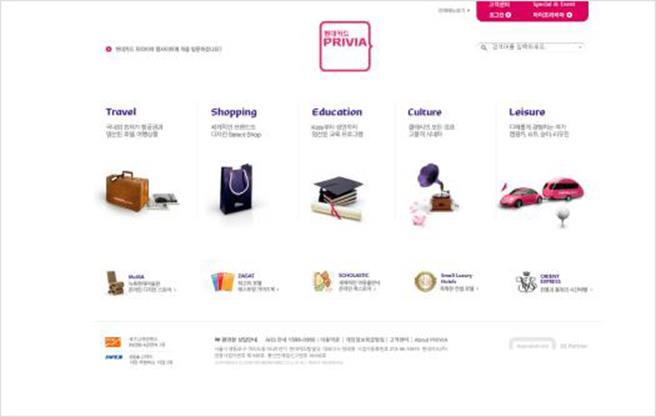
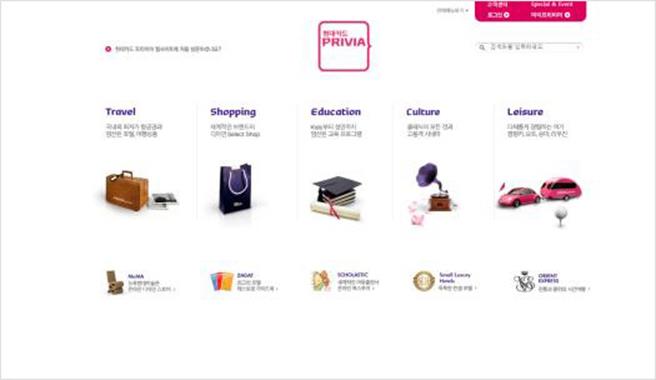
두 그림을 비교해 보면 FOOTER처리가 된 디자인이 훨씬 더 안정적이란 느낌이 들 것이다. 이는 FOOTER를 통해 밑으로 흘러가는 시선을 마무리 지어줌으로 사용자의 시선이 오른쪽으로 자연스럽게 흘러가면서 마무리 될 수 있으며, 마무리 되어주는 시점에 기업로고를 강하지 않으면서도 은은하게 보여줌으로써 편안한 마무리 처리가 가능하게 해주기 때문이다.
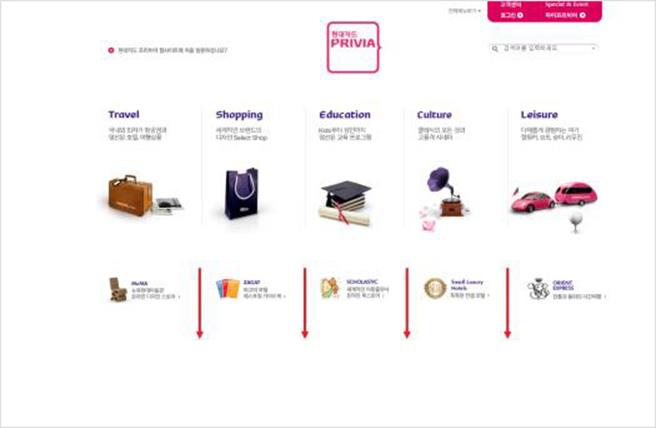
▲ 시선이 아래쪽으로 여러개 분산되어 나뉘어 지고 있는 모습
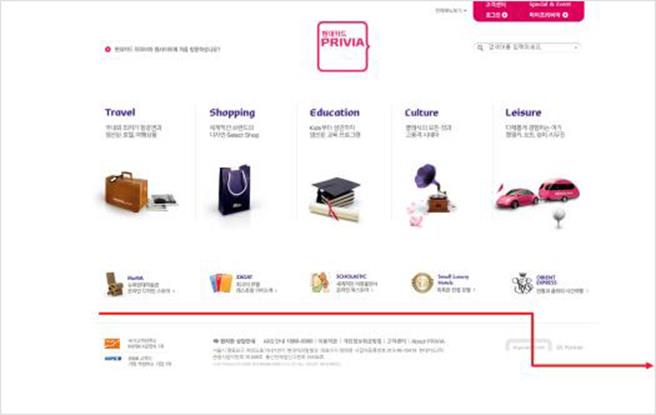
▲ 시선이 하단 FOOTER를 따라 흐르면서 오른쪽 로고에서 마무리되는 모습
이처럼 하단 FOOTER의 사용을 통해 디자인의 전체 균형을 안정화 시키고, 디자인을 좀 더 세련되게 마무리 할 수 있는데, 이것은 이 사이트처럼 FOOTER부분의 깔끔한 마무리가 전제되었기 때문에 가능한 것이라 볼 수 있다.
상단 콘텐츠를 방해하지 않는 배치된 로고와 메뉴 주소 COPYRIGHT부분의 적절한 여백 등이 조화롭게 배치되어 있는 가운데에서도 가독성을 크게 훼손하지 않는 범위 내에서 컬러 및 크기 조절이 세련되게 디자인 되어있다.
그렇다면 다음 그림들을 보고 여러분들은 어떠한 문제점들을 발견할 수 있겠는가?
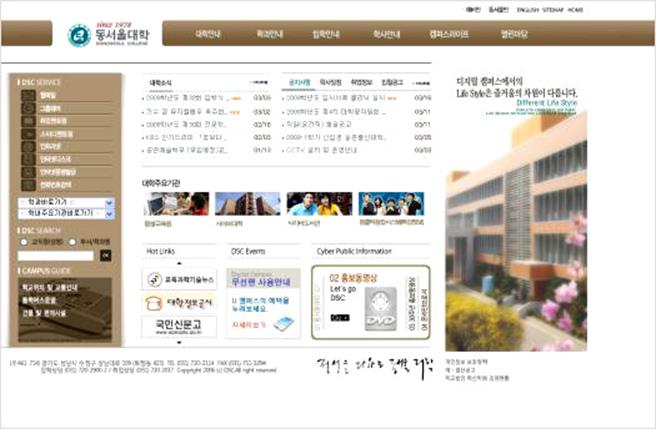
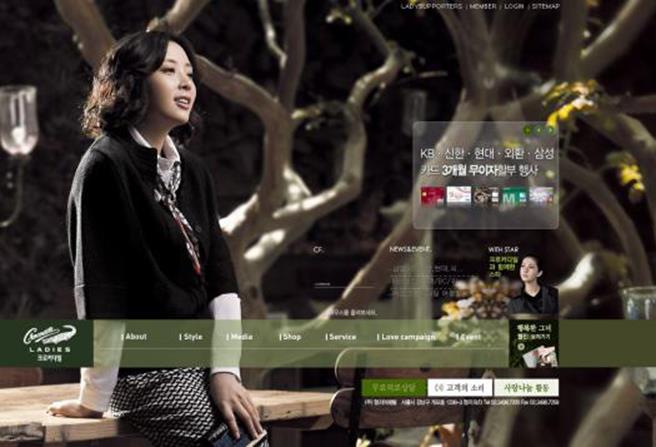
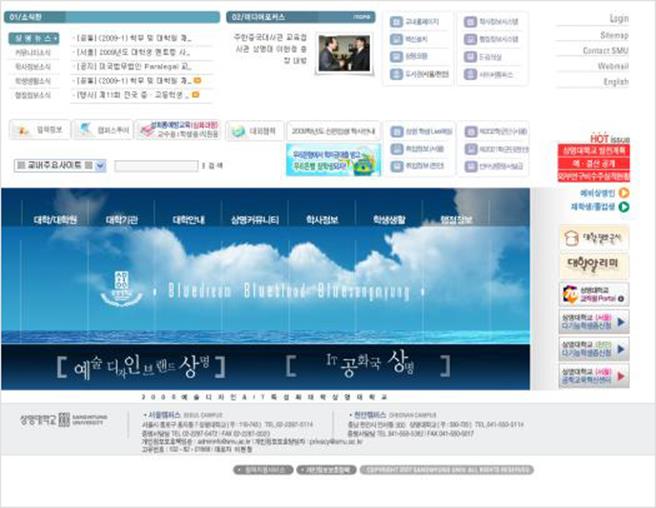
세 개의 사이트 모두 다 크게 흠잡을 만큼 디자인이 크게 떨어지는 것은 것은 아니지만 무엇인가 정리되지 않은 듯한 모습을 보여주면서 어수선한 분위기를 엿 볼 수 있다. 그렇다면 이 정리되지 않은 분위기는 무엇으로 인한 것인지 그 원인을 하나씩 살펴보도록 하자.
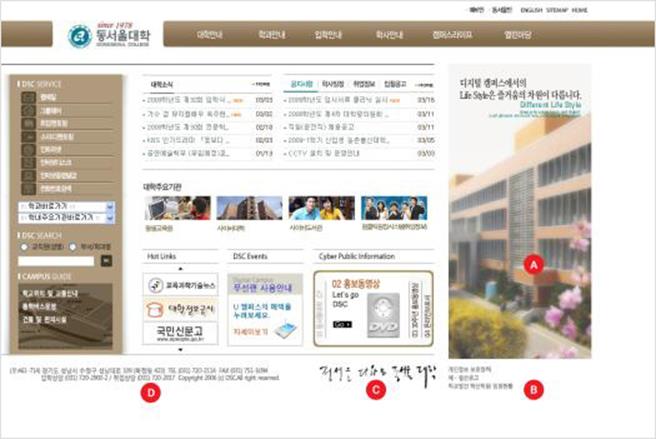
동서울대학 웹사이트에서 나타난 문제점을 살펴보면 비주얼을 차지하고 있는 A부문이 그리드를 무시한 채 하단 FOOTER까지 침범하여 화면이 우측으로 기운듯한 불안정한 구도를 보여주고 있으며, 이것이 결국 B의 Quick Menu까지 영향을 끼쳐 FOOTER의 범위까지 넘어서고 있다. 또한 전체적인 화면 디자인과 어울리지 않게 캘리그라피로 쓰여진 C 부분의 임펙트가 너무 강해 시선을 분산시키는 역효과를 발생시키고 있다.
마지막으로 D의 FOOTER 부분은 행간이 너무 좁고 좌우측으로 우편번호와 Copyright부분이 삐져 나옴으로써 안정된 느낌을 주지 못하고 있는 것이 큰 문제점이라 할 수 있다. 이렇듯 마지막 처리가 세심하고 깔끔하게 정리되지 못하다 보니 전체적인 퀄리티를 저해 하고 있음을 발견할 수 있다.
▲ ADDRESS와 COPYRIGHT부분에서 양쪽으로 글자가 삐져 나와 있는 모습
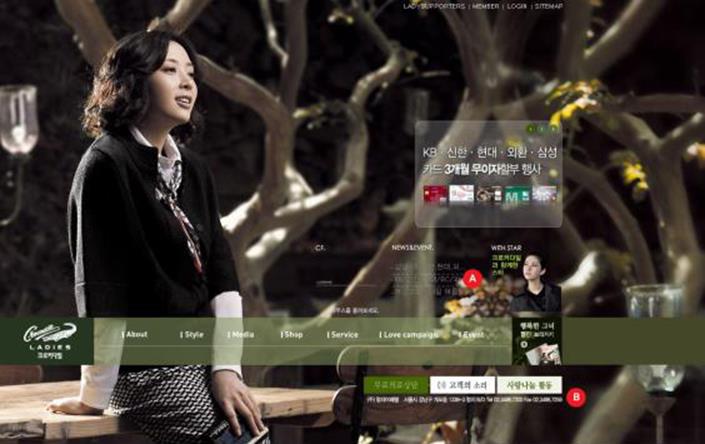
화면 중앙에 위치해 있는 NEWS/EVENT의 A부분이 FOOTER부분(B)에 비해 혼잡스럽고 선명하지 못해 역으로 FOOTER가 중요 콘텐츠인 A부분보다 강조되는 기이한 현상이 발생되고 있다.
A부분과 B부분의 컬러를 서로 바꾸었더라면 좀더 안정된 디자인이 되었을 것이다. 또한 B부분에서는 바로 위에 위치한 세 개의 배너와 같은 길이를 유지함으로써 안정된 정렬 상태를 보여주고 있지만 상단 콘텐츠들에서는 지그재그로 콘텐츠가 배치돼 혼란스러운 구도로 인해 불안정한 레이아웃을 연출하고 있는 것이 크게 흠이라 할 수 있다. 너무 배경 비주얼만을 강조한 채 나머지 요소들에 대해서는 깔끔한 마무리가 이루어 지지 못한 것이 매우 아쉽게 느껴지는 디자인이다.
상명대학교 사이트의 FOOTER부분은 가장 안정되고 세련된 디자인을 보이기는 하나 크게 3가지 문제점을 발견 할 수 있는데 우선 각각 캠퍼스별로 나뉜 ADDRESS부분에서 각 캠퍼스명을 기입한 곳에 처리한 블릿으로 인해 캠퍼스명이 들여쓰기가 됨으로써 깔끔한 정렬이 이루어지지 못하고 있으며 통합적으로 쓰인 개인정보책임 부분이 중앙의 선과 겹쳐지어 디자인 오류가 발생한 듯한 느낌을 주고 있다.
또한 GRAY톤의 배경으로 영역 처리된 FOOTER 영역 부분에서 상단 부분에 비해 하단 여백이 거의 없어 안정된 마무리를 못 보여주고 있는 것이 큰 흠이라 할 수 있다.
▲ footer 처리가 잘된 디자인들